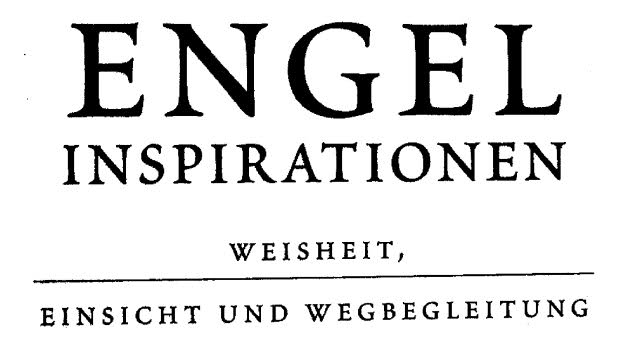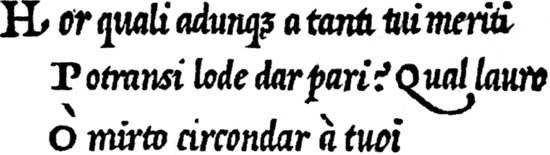
Ähnlich Minion, Bembo oder Sabon
What the font spuckt da ja die »Poetica Chancery IV« aus, die auch ziemlich dicht dran ist (einschließlich problematischer Kerning-Paare):
Wer kommt denn eigentlich auf die Idee einer solchen Mischung? Die Versalien gehen ja noch, aber bei der Kombination mit den Minuskeln fangen ja bei mir an, sich die Fußnägel abzulösen:
Wer kommt denn eigentlich auf die Idee einer solchen Mischung?
Früher (frühe Renaissance) war das offenbar nicht unüblich, kursive Versalien gab es nicht.
Die Macher der Rialto DF haben die Versalien in ihrer Nachbildung einer Renaissance-Schrift extra so gestaltet, dass sie sowohl für Aufrechte als auch für Kursive funktionieren (sollen). Sprich: verhältnismäßig klein und dezent geneigt. Bei der Rialto funktioniert das auch ganz gut (Kalligraphie-Duktus, ziemlich aufrechte Kursive, ziemlich geneigte Aufrechte), bei der Poetica offensichtlich eher weniger.
Bleibt halt die Frage, wie weit man solche Eigenheiten an die heutige Zeit anpassen möchte ... als Cancellaresca-Nachbildung ist es legitim.
Edit: ich sehe grade: die Variante III hat z.B. Swash-Versalien, die Variante II schräg gestellte Versalien. Insofern ist ein Satz mit aufrechten auf jeden Fall "gerechtfertigt".
Ja, eben, es gibt die entsprechenden Versal-Formen, das habe ich auch gesehen. Aber warum muß man dann die aufrechten Formen mit den kursiven kombinieren? Nein, das ist die falsche Frage, denn Deine Erklärungen habe ich schon verstanden. Es ist wohl eher so, daß ich die kursive Form, insbesondere im Zusammenhang mit den aufrechten Versalien, für ziemlich verunglückt halte. In Deinem Beispiel bildet gerade das »Q« z.B. ein sehr schönes optisches Gegengewicht zur Kursiven, fällt also gar nicht so sehr heraus sondern rundet eher ab. Vergleich das doch mal dem aufrechten »E«, den kursiven Gemeinen und dann diesem kursiven »g« bzw. noch schlimmer »p«. Da hat es sich im kalten Europa geneigt und rutscht auf dem Eis noch schön aus. Diese weggebogene Unterlänge schafft eben genau **kein** Gegengewicht zur kursiven, welche den Kontrast zu den aufrechten Versalien noch mildert, sondern macht das ganze noch viel schlimmer. Ich kann mir einfach nicht helfen, mein Sinn für Ästhetik fühlt sich da etwas gekränkt, denn in der komplett kursiven Gestaltung (Nr. II z.B.) sind die Formen generell ja eigentlich nicht so verkehrt (auch wenn es m.E. Schöneres auf dem Markt gibt).
Na, wenn es reiner Versalsatz wird und per Hand die Buchstabenpaare ausgeglichen werden, dann ist gegen die Peotica auch nichts einzuwenden! :wink: